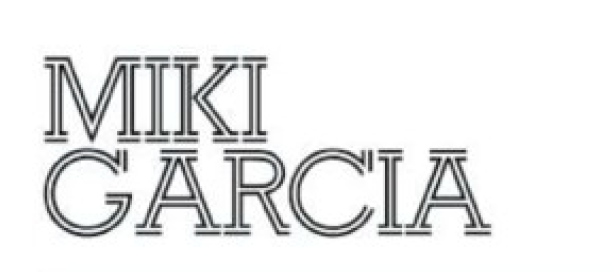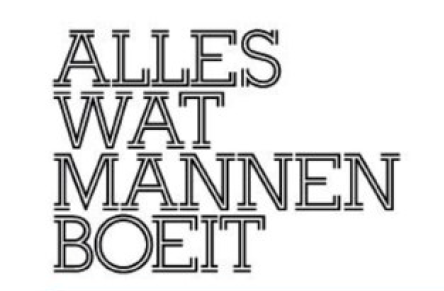
Headlineschrift aus Linien
hm, erinnert mich an die Memphis, aber die kenn ich nicht in als inline-Schnitt.
Ich habe die Schrift im Sommer in der niederländischen Ausgabe des Playboy entdeckt. Dort wurde sie auf mehreren Seiten verwendet ... der Playboy lag in einem Café aus und ich habe leider nur zwei Fotos der Schrift gemacht.
Aus einem gescannten Playboy (Nr. 9/2011):
Ich habe die Schrift im Sommer in der niederländischen Ausgabe des Playboy entdeckt. Dort wurde sie auf mehreren Seiten verwendet ... der Playboy lag in einem Café aus und ich habe leider nur zwei Fotos der Schrift gemacht.
hm, bei ›ärmeren‹, unbekannteren zeitschriften hätte ich mir vorstellen können, dass es eine frei verkäufliche schriftart ist. beim playboy würde ich dagegen davon ausgehen, dass das eine handgeschnitzte variante der memphis ist. lasse mich allerdings gerne widerlegen.